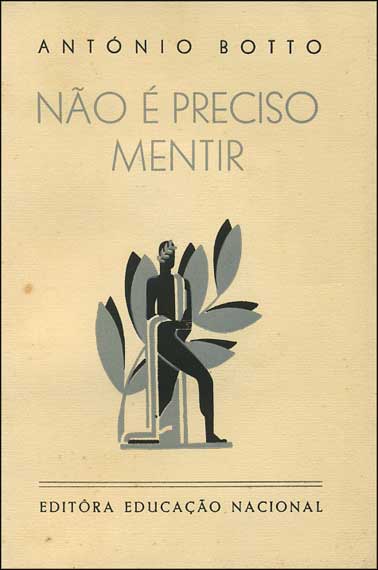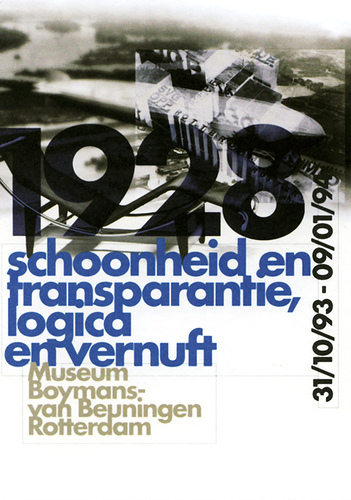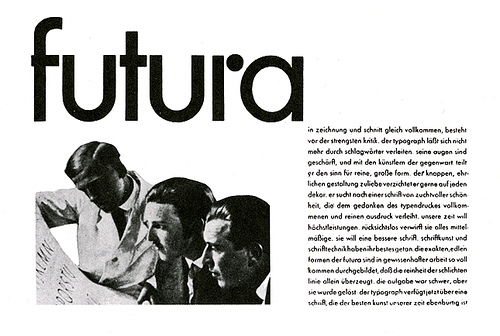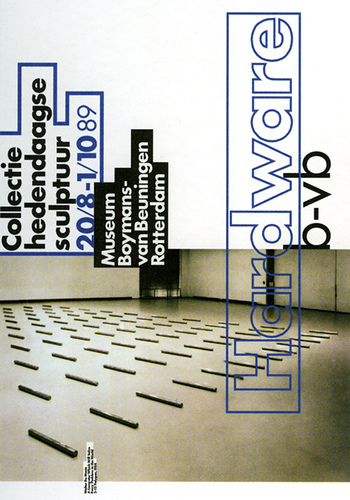
Futura (1924-26)O grande sucesso tipográfico foi (quase) um plágio de outras fontes grotescas já vigentes na época: da Erbar Grotesk e da Kramer (Frankfurt)...
Entre as sem serifas mais notáveis da época entre a Primeira e a Segunda Guerra Mundial, está a fonte Futura. Desenhada entre 1924 e 1926 por Paul Renner, é uma letra bem representativa da clareza defendida nos manifestos da Bauhaus, com evidente construção geométrica. Sóbria, neutral, clara, elegante, bem equilibrada, legível (em corpos grandes, mas também em texto corrido, a Futura apresenta as características preferidas pelos designers vanguardistas dos anos 20 e 30. Parece construída com régua e compasso, e as versões preliminares têm óbvias afinidades com as experiências tipográficas do anos 20. Mas assim como a Gill Sans (a outra importante sem serifa da época) se inspirou directamente no tipo que Edward Johnston desenhara para os transportes urbanos londrinos, também a Futura foi derivada de letras já existentes, por exemplo da Kramer-Grotesk, uma sem serifa desenhada pelo arquitecto alemão Ferdinand Kramer para uso do município de Frankfurt am Main, em todas as suas publicações. Outra letra que terá servido de modelo e inspiração foi a Erbar Grotesk, desenhada por Jakob Erbar para a Fundição Ludwig & Mayer (a partir de 1922), da Mergenthaler Linotype e da Linotype Londres. Segundo os depoiamentos e as interpretações que não insinuam o plágio da Kramer ou da Erbar, a inspiração da Futura teria vindo das inscrições lapidares da Grécia clássica, que Renner analisou em pormenor. Os gregos usavam uma letra sem serifas de formas simples, e teria sido essa clareza estética que Renner captou.
Os desenhos originais de Renner para a Futura estão hoje guardados na Fundición Tipográfica Neufville, sediada em Barcelona. Outro tipo sem serifa desenhado por Renner foi a Topic ou Steile Futura, uma variante condensada, com traços redondos nas letras A, E, M e W. Esta Topic foi editada pela Bauersche Giesserei já mais tarde, em 1953.
Hoje existem muitas «Futuras» de estética questionável: atenção às versões grátis. Fontes similaresA Nobel
A Avenir